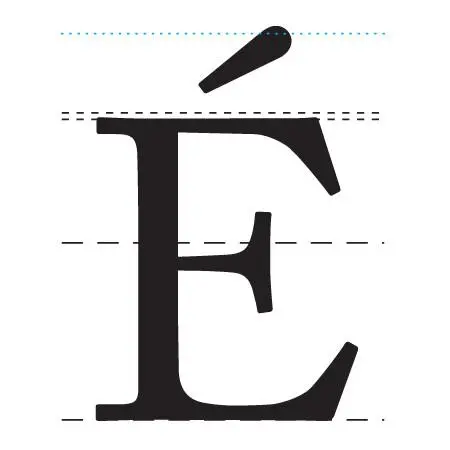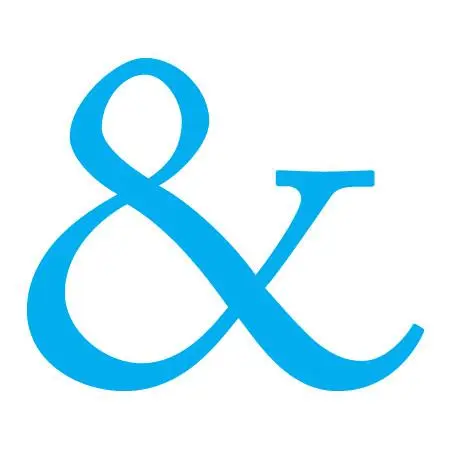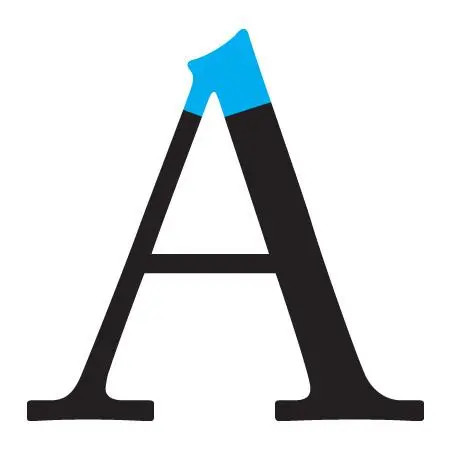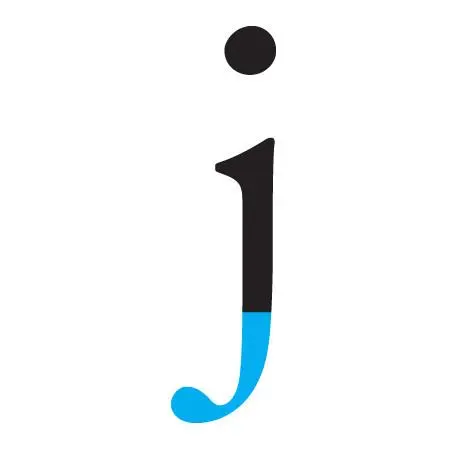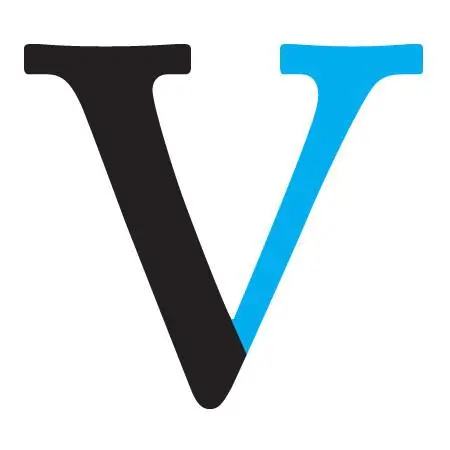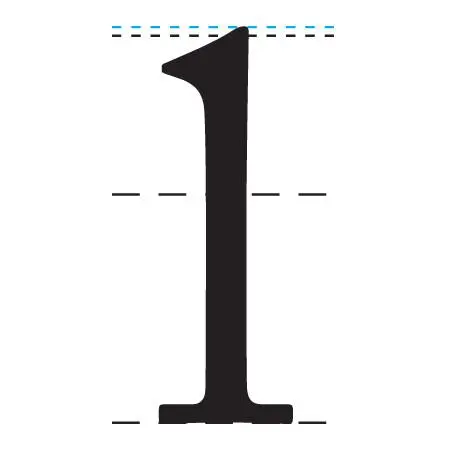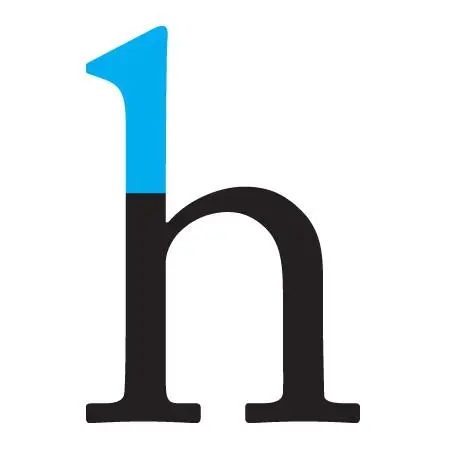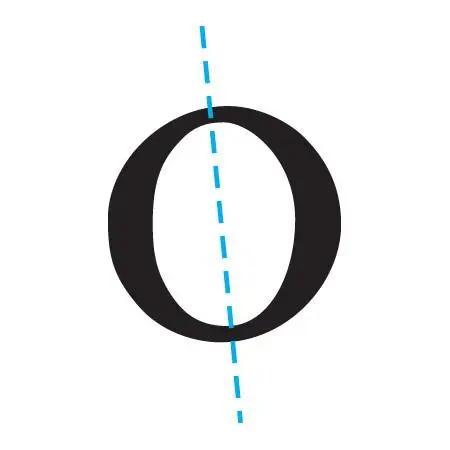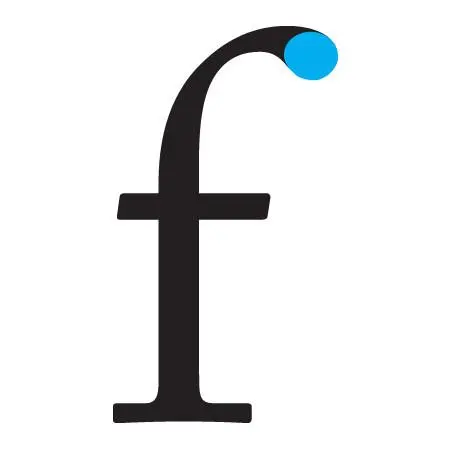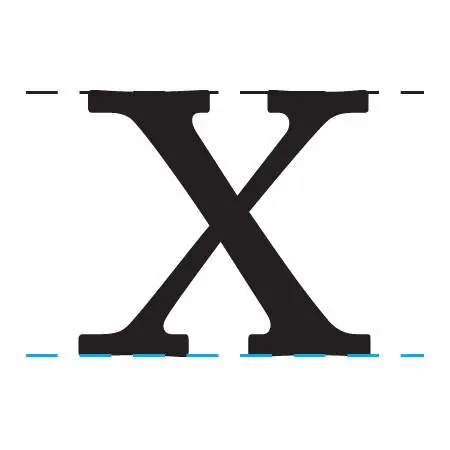
Đối với người nghiên cứu, khi tìm được 1 tài liệu quý, giống như tìm được 1 cánh cửa thần kỳ. Chúng ta có thể sử dụng cách nói như vậy đối với tài liệu dưới đây.
Baseline
X-Height
Mean-Line
Ascender
Ascender-Line
Acent-Line
Descender
Descender-Line
Descent_Line
Lowercase
Uppercase
Italics
Cap-Height
Cap-Line
Body-Height
Apex
Vertex
Counter
Open-Counter
aperture
Terminal
Teardrop-Terminal
Ball-Terminal
Finial
Flag
Arm
Cross-Stroke
Crossbar
Serif
Bilateral Serifs
Ampersand
Arc-of-Stem
Axis
Beak
Bowl
Bracket
Crotch
Diacritic
Diagonal-Stroke
Dot (Tittle)
Ear
Eye
Hairline
Hook
Leg
Ligature
Link
Lobe
Loop
Old-Style-Figures
Overshoot
Quaint
Shoulder
Spine
Spur
Stem
Stroke
Swash
Tail